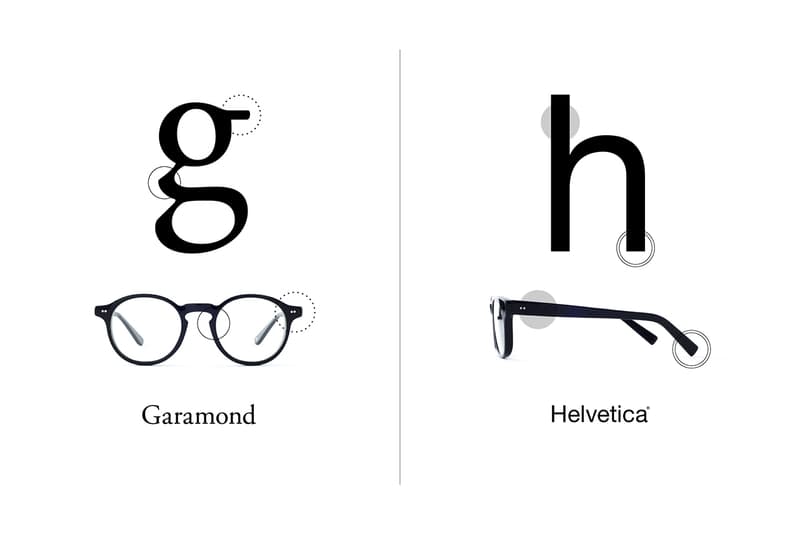
TYPE x Oh My Glasses 联名眼镜系列
TYPE 近日与日本眼镜品牌 Oh My Glasses
TYPE 近日与日本眼镜品牌 Oh My Glasses 展开合作,打造了一个全新的全新眼镜系列。顾名思义,这一系列眼镜产品的设计灵感都来源于和打字有关的元素。其实,这样讲还不是很确切,应该说是和我们平日里最熟悉的字体有关才对。大家都知道,在英文字符里分衬线和非衬线两种字体,而这两者在设计上有著截然不同的理念。Oh My Glasses 正是将这两种不同的设计理念融入到了镜架的设计中。目前发售的 TYPE 系列眼镜共有两款,分别从 Garamond 和 Helvetica 上获得了不少设计灵感。Garamond 款具有符合字体特征的圆形框架,而 Helvetica 款则在脚架尾端等处展现了字体的特色。除了款式之外,在镜架的颜色和材质的厚重度上,Oh My Glasses 同样为消费者提供了丰富的选择。有兴趣的朋友可以在跳转后查看详情。